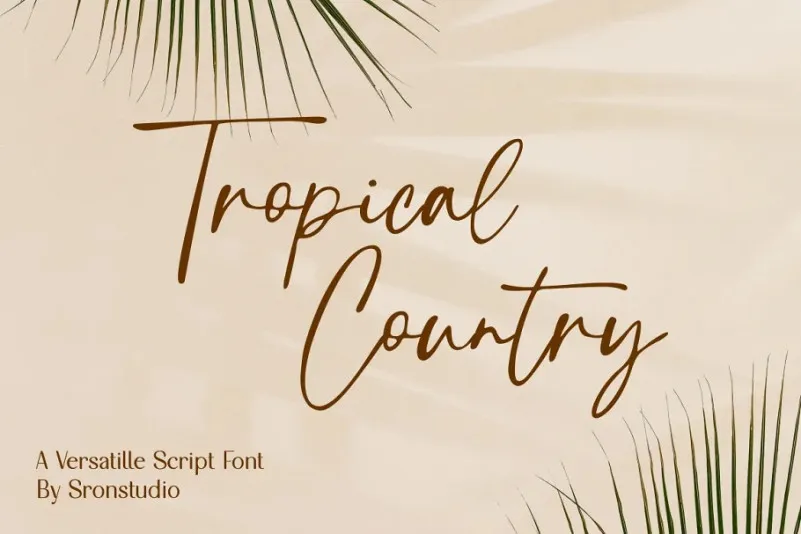
Esta font é uma assinatura script feita à mão, com um fluxo natural e fluido. Ela foi criada pelo designer Sronstudio e está perfeitamente adaptada para diversas finalidades gráficas, incluindo marcas de marca, convites, materiais de estação, designs de casamento, posts nas redes sociais, anúncios, embalagens de produtos, design dos próprios produtos, etiquetas, fotografia e até mesmo como água-marinha para eventos especiais. A fonte é perfeita para decorar o seu trabalho gráfico com um toque autêntico e delicado da natureza tropical brasileira.